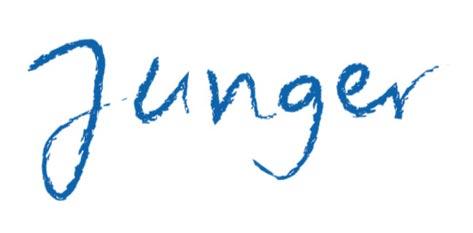
Welche Kreideschrift könnte das sein? (Junger BLLV)
ich bin auf der Suche nach dieser Kreide-Schriftart. Kann mir da jemand weiterhelfen?
leider weiß ich darüber nicht sehr viel. Dieser Schriftzug ist Bestandteil des Logos  des "Jungen BLLV"  (BLLV = Bayer. Lehrer- und Lehrerinnenverband). Ein Mitglied hat mich gebeten dieses Logo, das mir nur als jpg-Datei vorliegt  zu vektorisieren. Ich habe das schon über Illustrator  gemacht, aber das Ergebnis des Teils "Junger"  lässt du wünschen übrig. Ich denke, es handelt sich um einen ganz  normalen Font-Schriftzug, konnte ihn aber bisher nicht finden.
ich glaube nicht, dass der Schriftzug aus einer Satzschrift erzeugt wurde. Vielmehr deutet die Struktur und Form des Strichs darauf hin, das hier z.B. mit Illustrator und einer Pinselkontur gearbeitet wurde. Darüberhinaus scheint es ja auch keine weiteren bekannten Anwendungen in dieser "Schriftart" zu gehen, oder?
@Martin: Ja, wahrscheinlich hast du recht mit der Vermutung, dass diese Schrift mit einer Pinselkontur gezeichnet wurde.
@Ralf: Danke, ich habe online nach Logos gesucht, aber dieses recht gute ist mir nicht untergekommen. Danke, da wird das Vektorisierungsergebnis recht passabel. Das muss reichen.